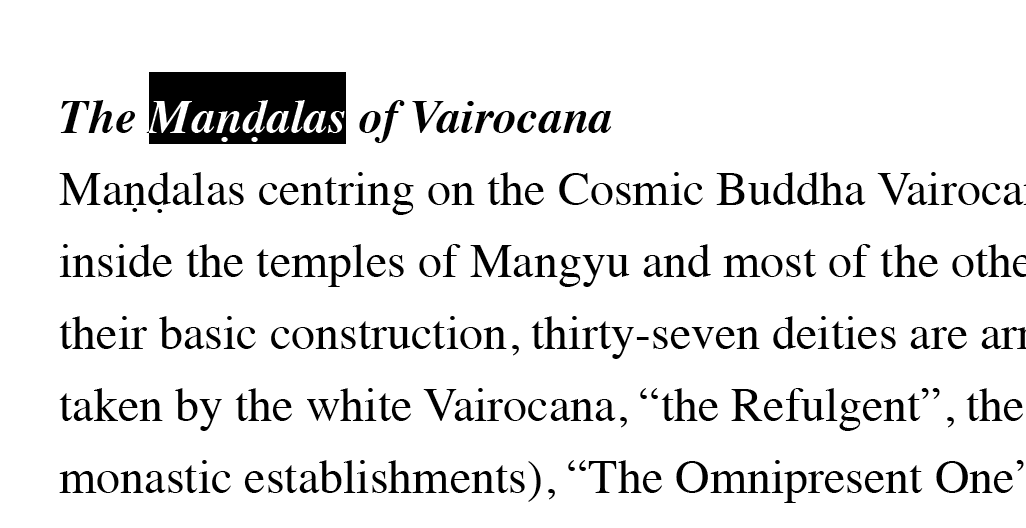
Schrift mit vielen Sonderzeichen
Ich muss einen Text setzen mit sehr vielen unterschiedlichen Sonderzeichen und ich hatte mich auch erst für die sehr gut ausgebaute ARNO PRO entschieden bis ich gemerkt habe, dass sie 2 spezielle Sonderzeichen nicht unterstützt ( ein "n" mit einem Punkt darunter und ein "d" mit einem Punkt darunter).
Bei der Suche nach einer Grotesk Schrift für den Text (für die Bildunterschriften) ist die Suche genauso deprimierend.
Bisher habe ich nur die TIMES als Antiqua und die ARIAL als Grotesk gefunden, die alle Sonderzeichen in dem Text unterstützen.
Jetzt meine Frage:
Kennt vielleicht jemand weitere Antiqua und Grotesk Schriften, die speziell diese beiden Sonderzeichen unterstützen?
Ich hätte einfach gerne eine grössere Schriftauswahl für das Projekt.
Das Thema hatten wir hier gerade ganz ähnlich. Schwalbenkönig und ThierryM haben einige Schriften genannt :D
Sorry, wenn ich dieses alte Thema nach 3 Jahren wieder ausgrabe, aber ich finde unter dem angegebenen Link leider nicht den erhofften Beitrag. Auch in der Forensuche finde ich Ihn nicht. Vielleicht kann mir da jemand einen neuen Link geben?
Ich bin auf einer ganz ähnlichen Suche: welcher Font (u.U. sogar frei verfügbar) ist mit ähnlich vielen Sonderzeichen ausgestattet, wie Arial, Tahoma, Verdana oder Sergeo UI und erfüllt meine typografischen Ansprüche :-)
Unicode enthält etliche fertig zusammengesetzte Zeichen mit Punkt darunter (allerdings, soweit mir bekannt ist nicht n und d) und kann beliebige Zeichen mit Punkt darunter durch Nachstellen eines kombinierenden Punktes (Unicode U+0323) darunter darstellen.
... meine typografischen Ansprüche ...
Was heißt das genau?
... und wie passt das mit dem zusammen:
... (u.U. sogar frei verfügbar) ...
Was heißt das genau?
... und wie passt das mit dem zusammen:
Unicode enthält etliche fertig zusammengesetzte Zeichen mit Punkt darunter (allerdings, soweit mir bekannt ist nicht n und d) und kann beliebige Zeichen mit Punkt darunter durch Nachstellen eines kombinierenden Punktes (Unicode U+0323) darunter darstellen.
Ich glaube d und n mit Punkt darunter sind: 1E0D und 1E47
Wenn's Sanskrit sein muss: URW Palladio ITU sollte das haben.
Nachtrag: Wenn ich mir meine Zeichentabelle so anschaue, ist das sogar recht verbreitet ... :-)
Es soll Text gesetzt werden, der nicht sprachenbedingt Sonderzeichen enthält, sondern um dem Leser Betonungen hauptsächlich von Eigennamen anzuzeigen.
Daher ist es mir nicht möglich die Sonderzeichen auf eine bestimmte Sprache einzugrenzen.
Bisher sind mir folgende untergekommen:
ẹ ụ ạ ị ọ
auch: ó ē ḗ í
sowie:
ʼ (Modifizierender Apostroph)
ʽ (Modifizierendes gespiegeltes Komma)
ḗ : (e mit Makron und Akut)
Jedoch weiß ich nicht, was noch auf mich zukommt, daher wünsche ich mir größtmögliche Flexibilität.
Darüber hinaus enthält das Manuskript hebräische und griechische Passagen.
Hierbei gehe ich bisher davon aus, auf einen zweiten und dritten Font zurückgreifen zu müssen.
Es kommen keine arabischen, nepalesischen , chinesischen oder andere Sprachen vor.
Dass ich im Satz typografische Ansprüche mitbringe, kann man doch sicher nachvollziehen.
Dass ich professionelle Fonts nicht gratis hinterhergeworfen bekomme, ist auch klar. Und doch ist es nicht vollständig auszuschließen, auch umfangreich ausgestattete und detailliert hergestellte Fonts professioneller Natur gratis zu erhalten. Deshalb schrieb ich ja auch in Klammern „u.U.“, was doppelt eingesteht, dass sich dahinter keine Erwartungshaltung verbirgt. Nur wer freut sich nicht darüber, wenn es bspw. eine bereits vorhandene Myriad Pro getan hätte, was sie meines Erachtens derzeit nicht macht. Der Regular Schnitt macht zwar vieles mit, aber der Light Schnitt nicht mehr – um nur ein Beispiel zu nennen.
Nicht frei, aber sehr umfangreich, ist die Alphabetum, die auch über einen riesigen Demofont verfügt. Am Monitor ist sie nicht soooo hübsch anzuschauen, doch im Druck ist sie in Ordnung. Zudem ist die Lizensierungsgebühr mit 30 Euro sehr erträglich, wenn nicht gar nur symbolisch :)
Okay, das hatte ich nicht gesagt, für den Monitor benötige ich sie nicht. Danke!
Hast Du Dir schon mal die schön kernige Fedra angesehen? Die könnte man bei Bedarf auch mit anderen (Sprach)-Varianten ausbauen.
Edit: :oops:  Die hinkt wieder auf dem hebräischen Bein.  :shock:
Hast Du Dich mit Deiner Aufgabenstellung schon mal an die einschlägigen Fontanbieter (Fontshop, Linotype) gewandt?
Das Akut-Makron-e ist mir jedoch bisher nirgends untergekommen. Aber wäre es nicht einfacher, sich solche »Spezialzeichen« aus den vorhandenen Glyphen der Textschrift in InDesign über GREP & Co automatisiert zusammen zu stellen?